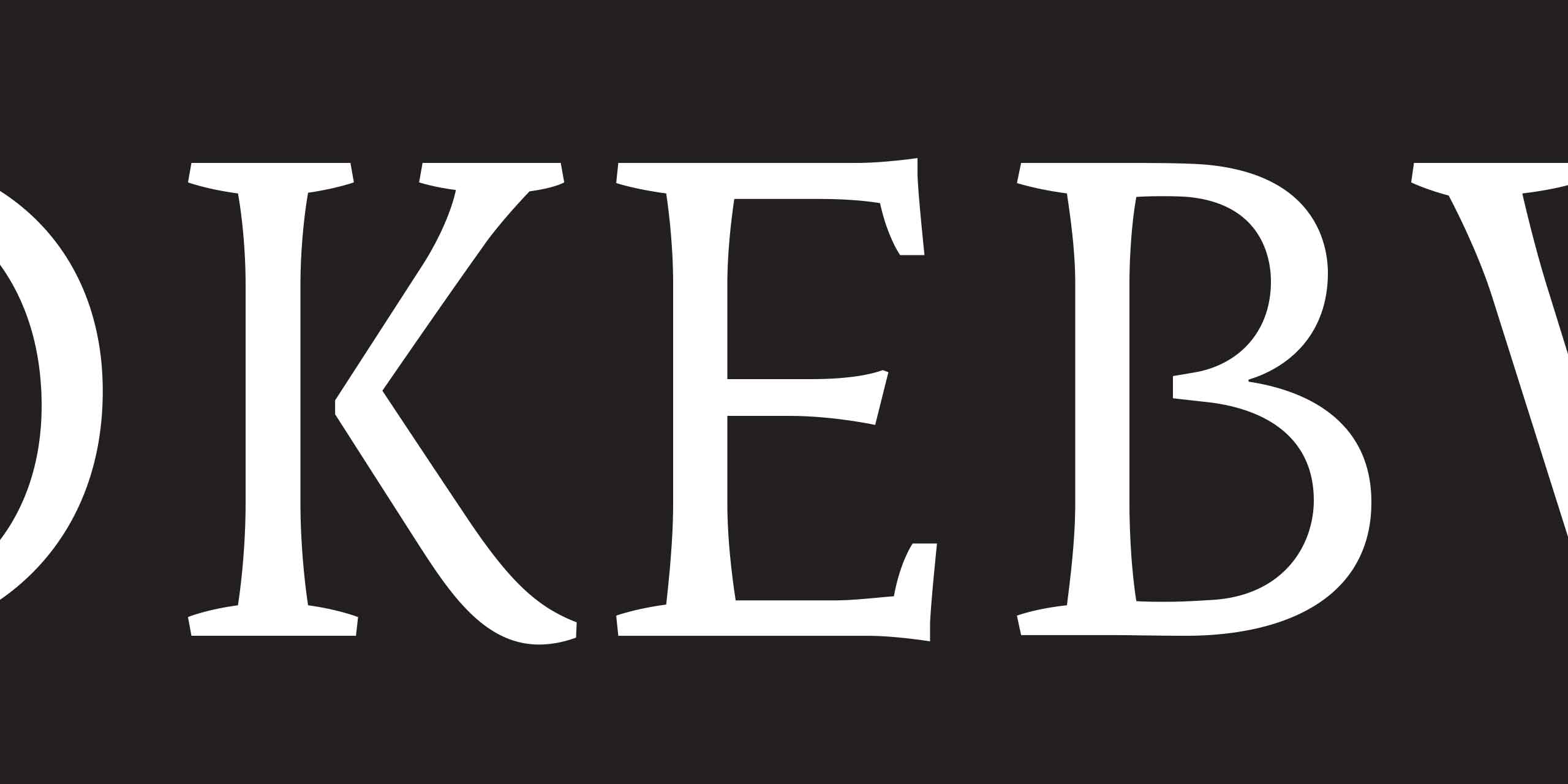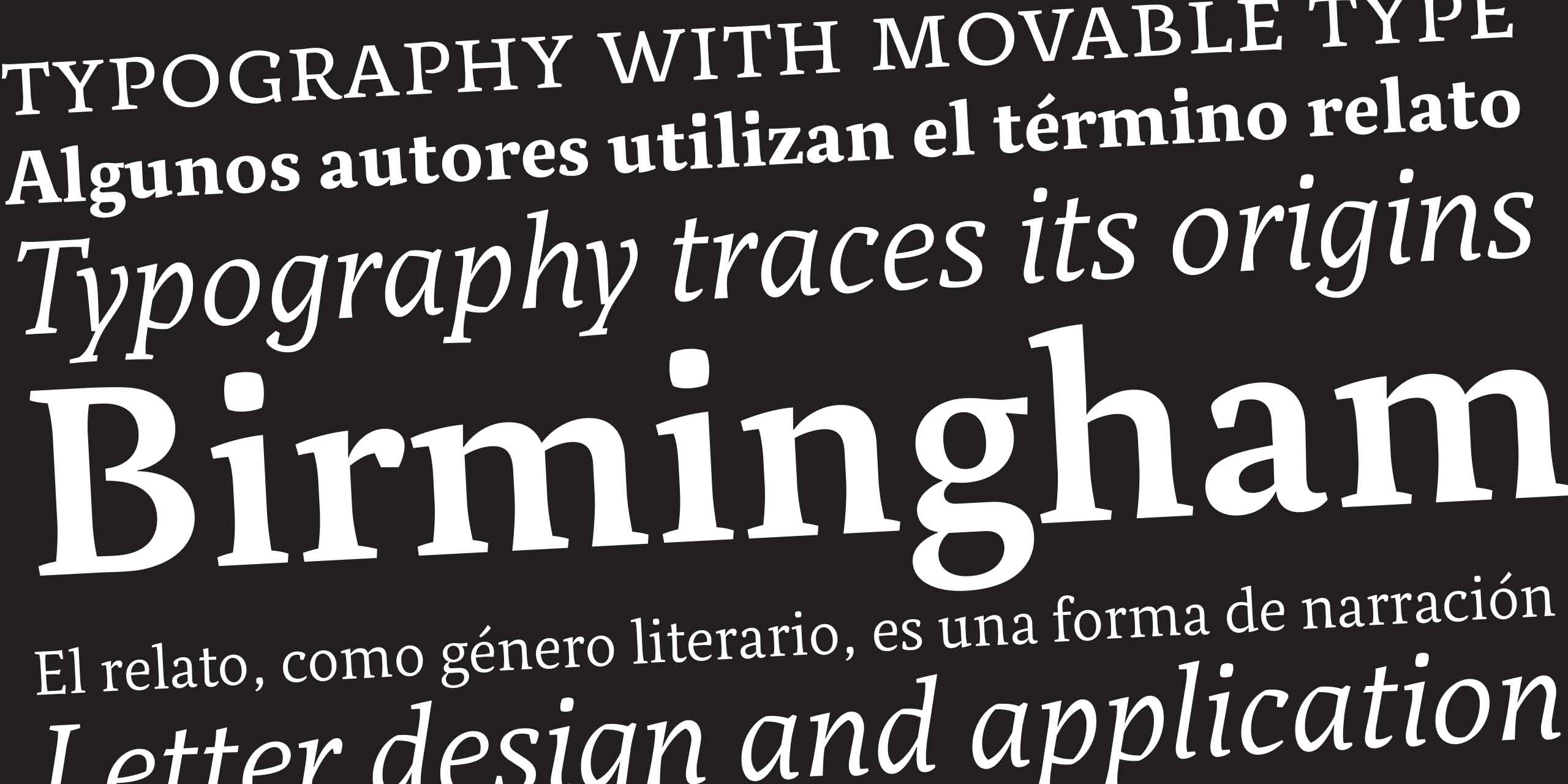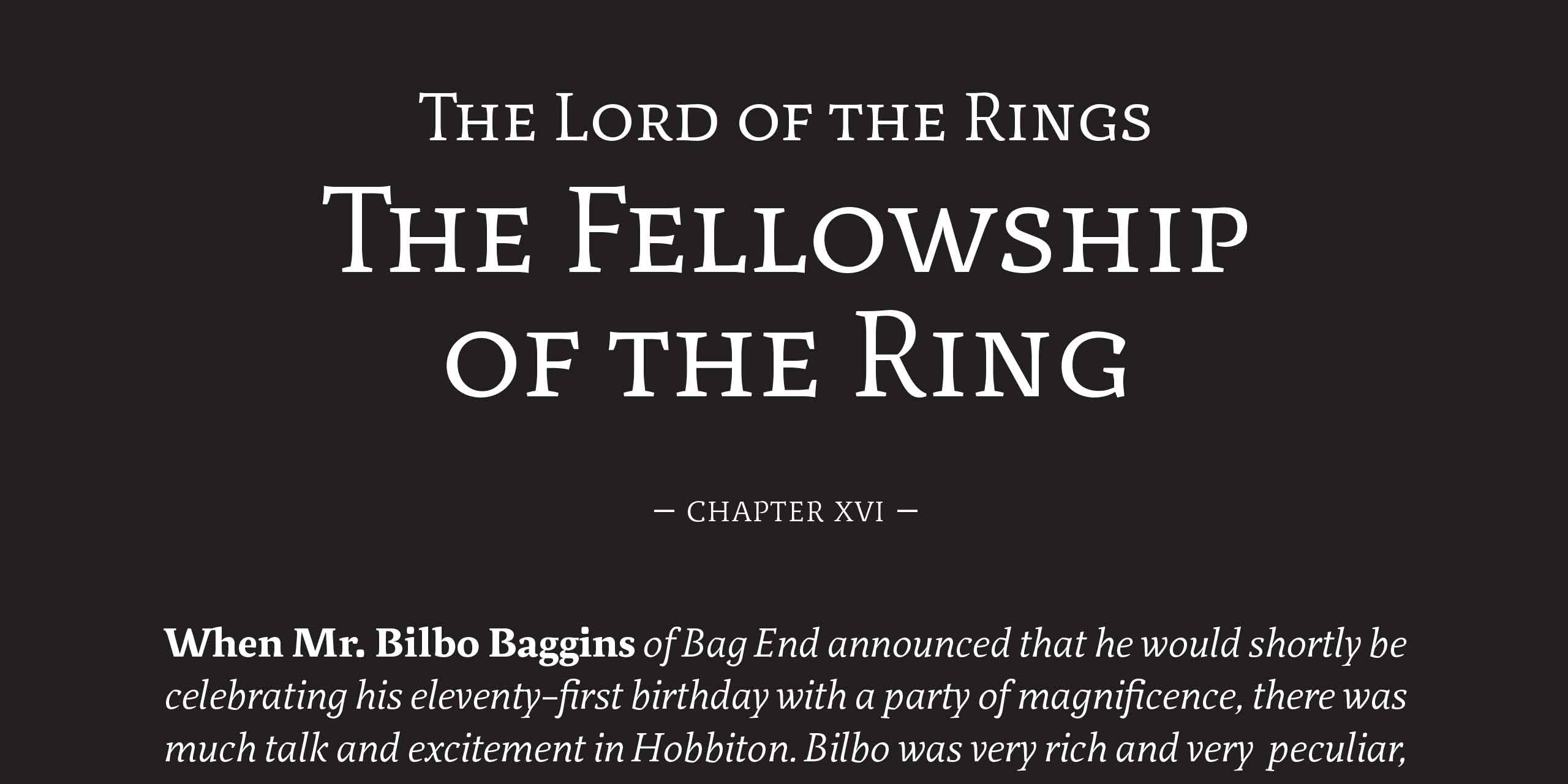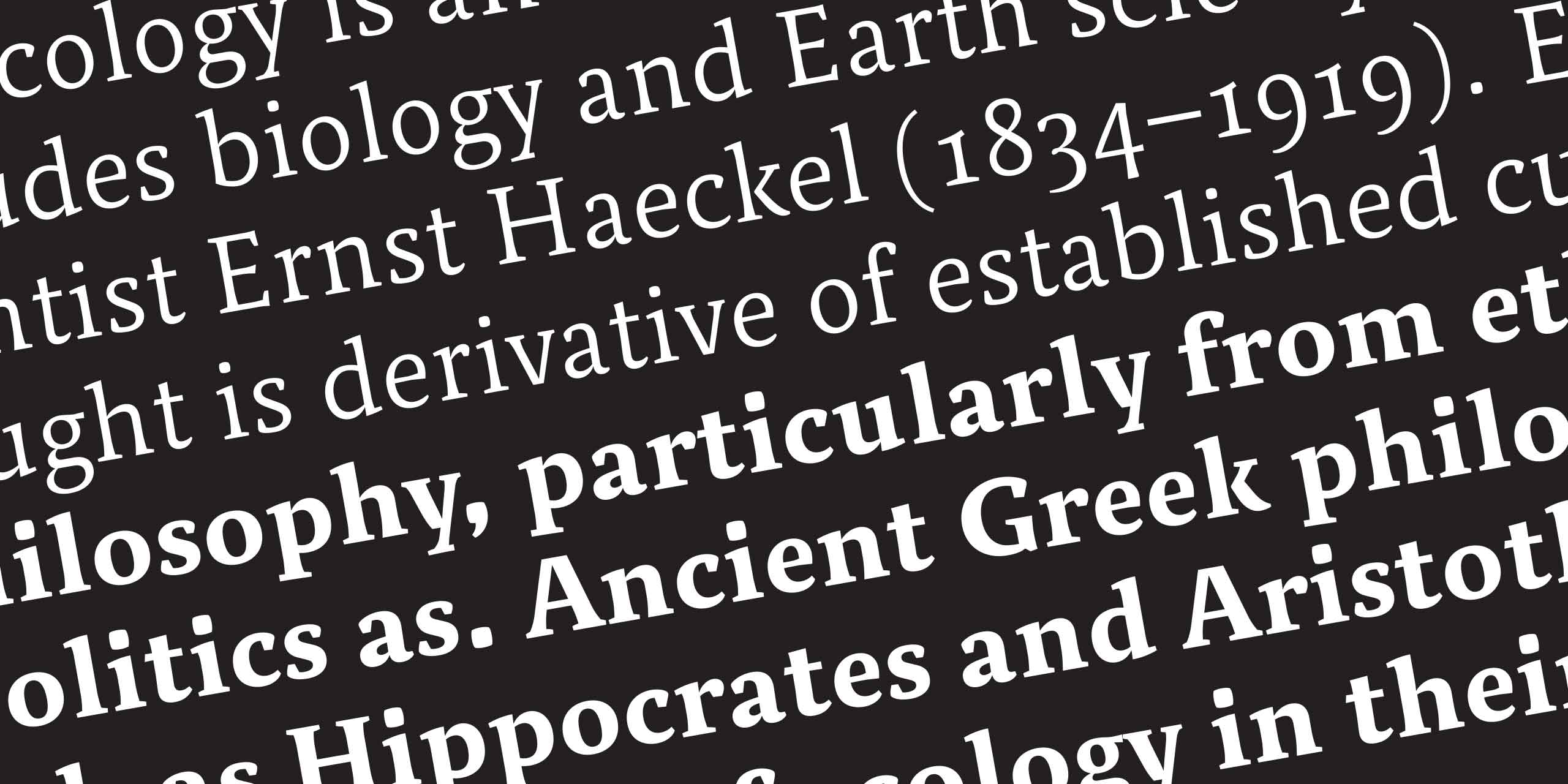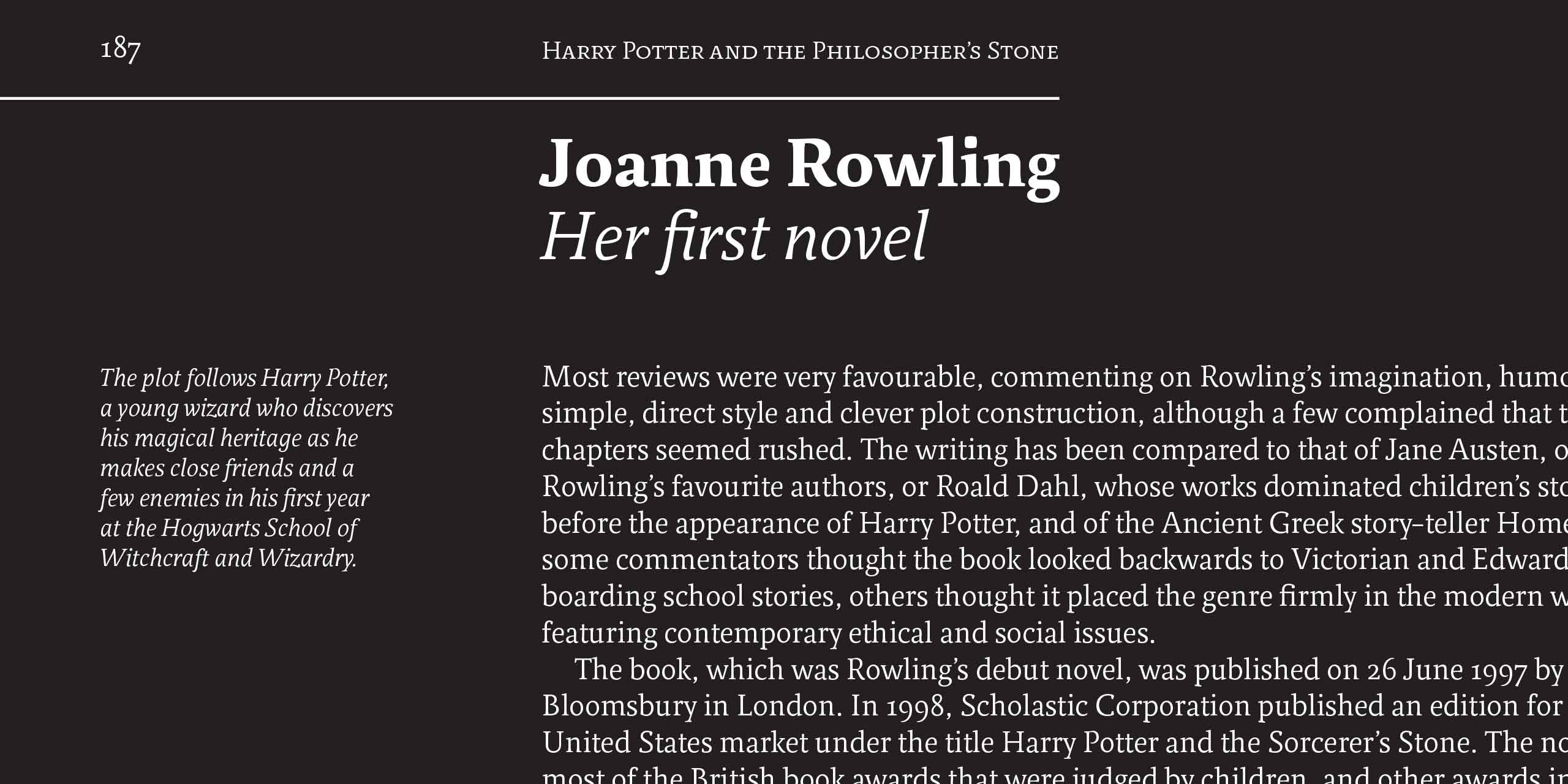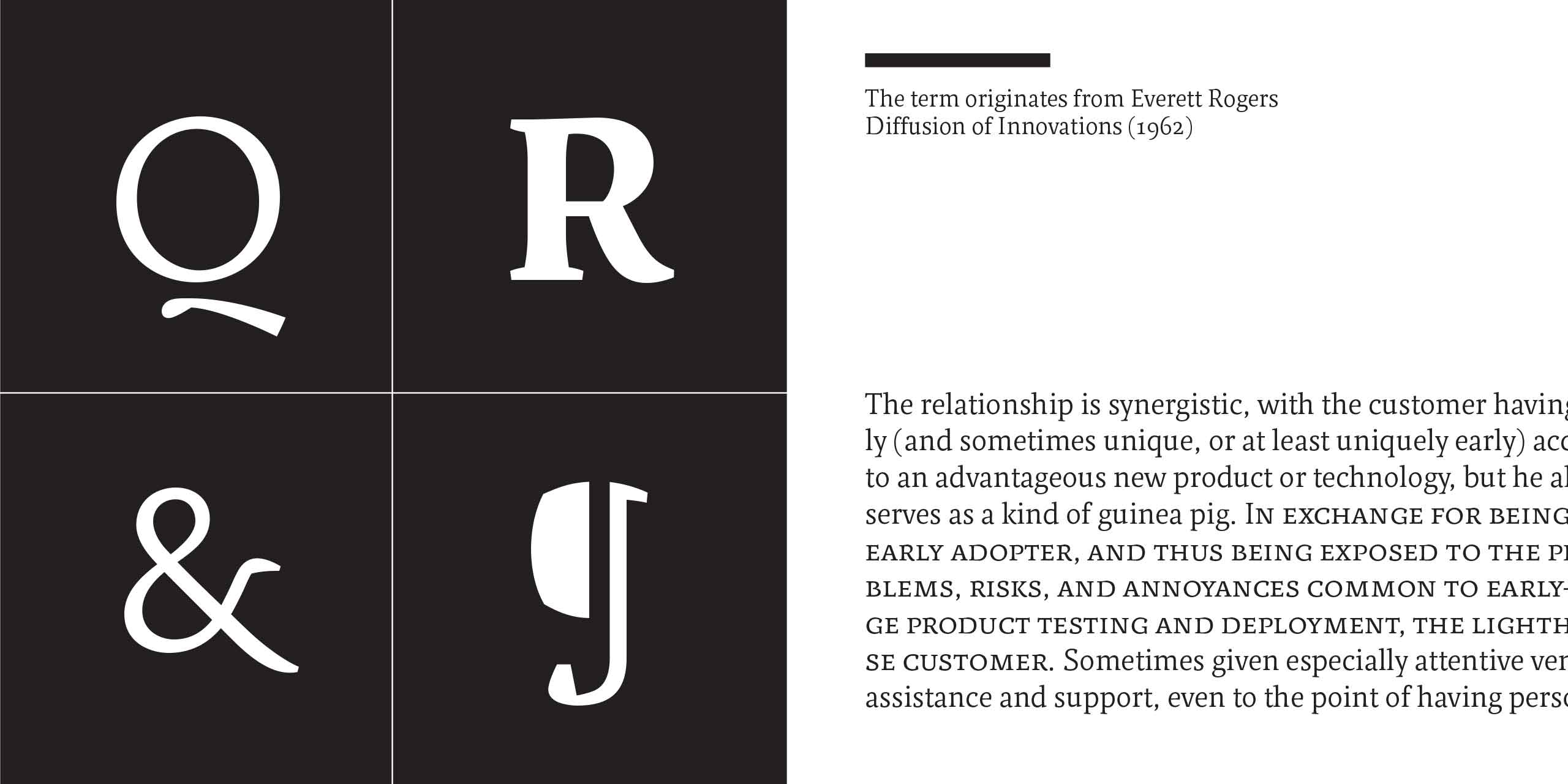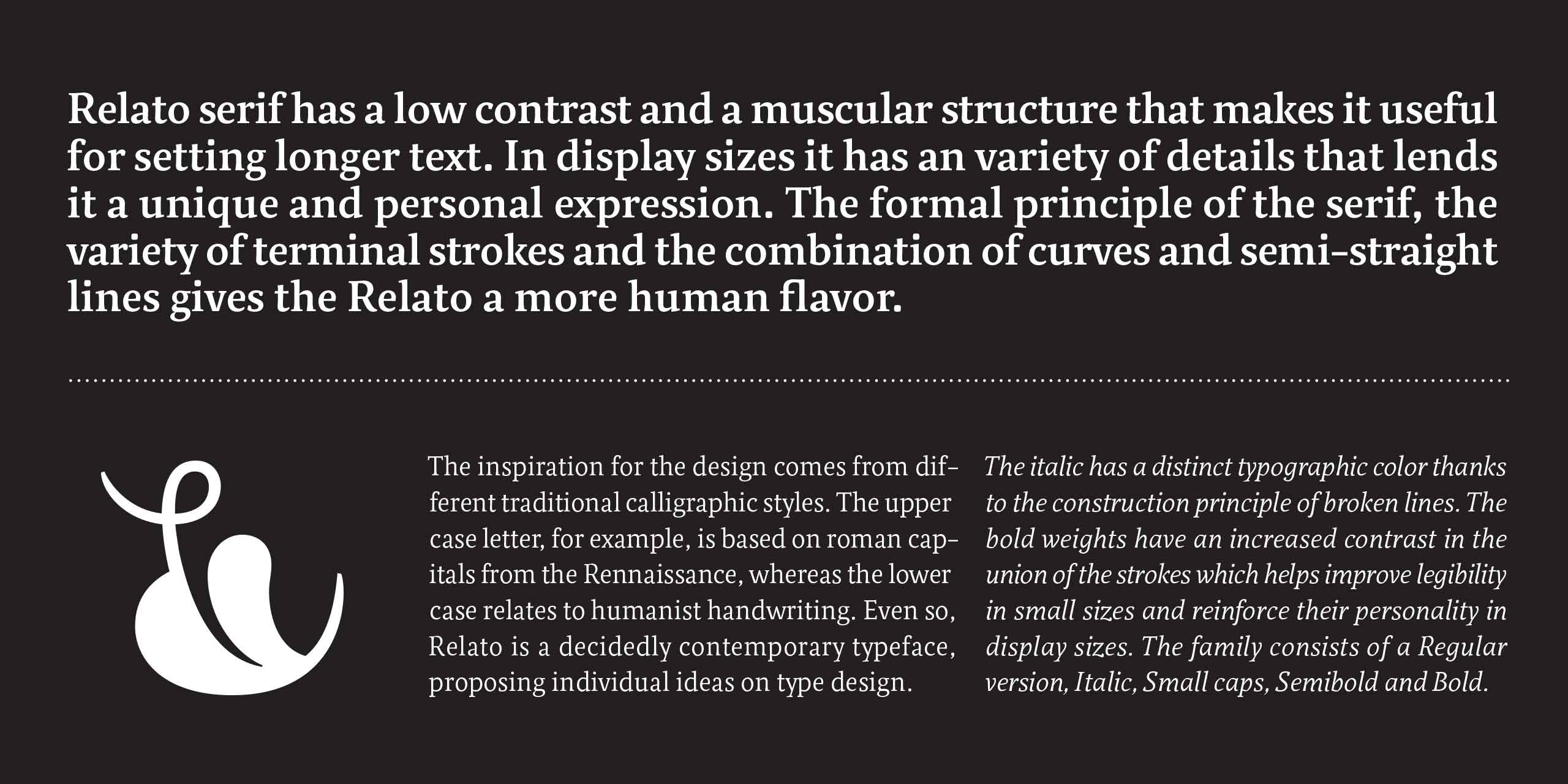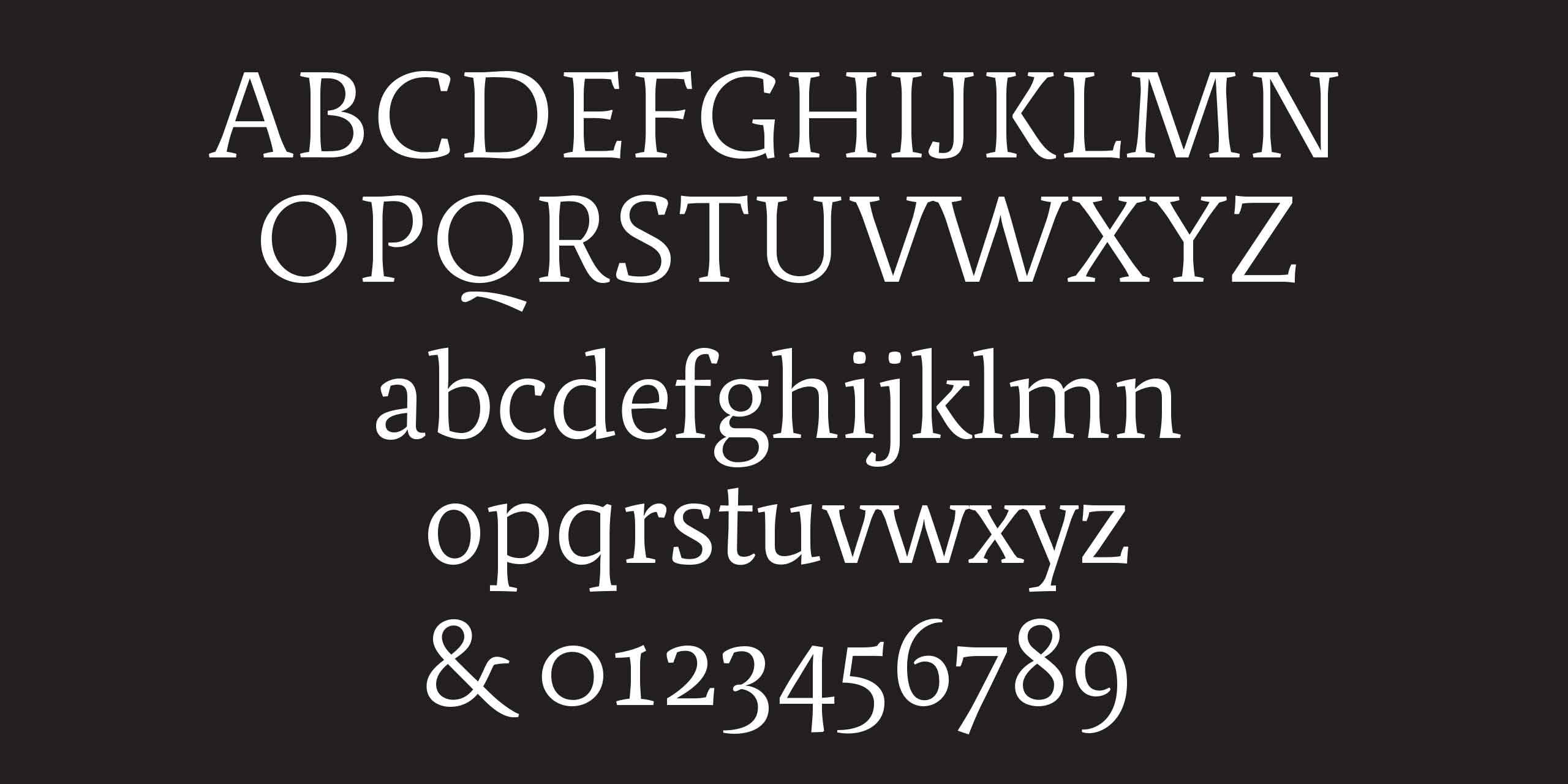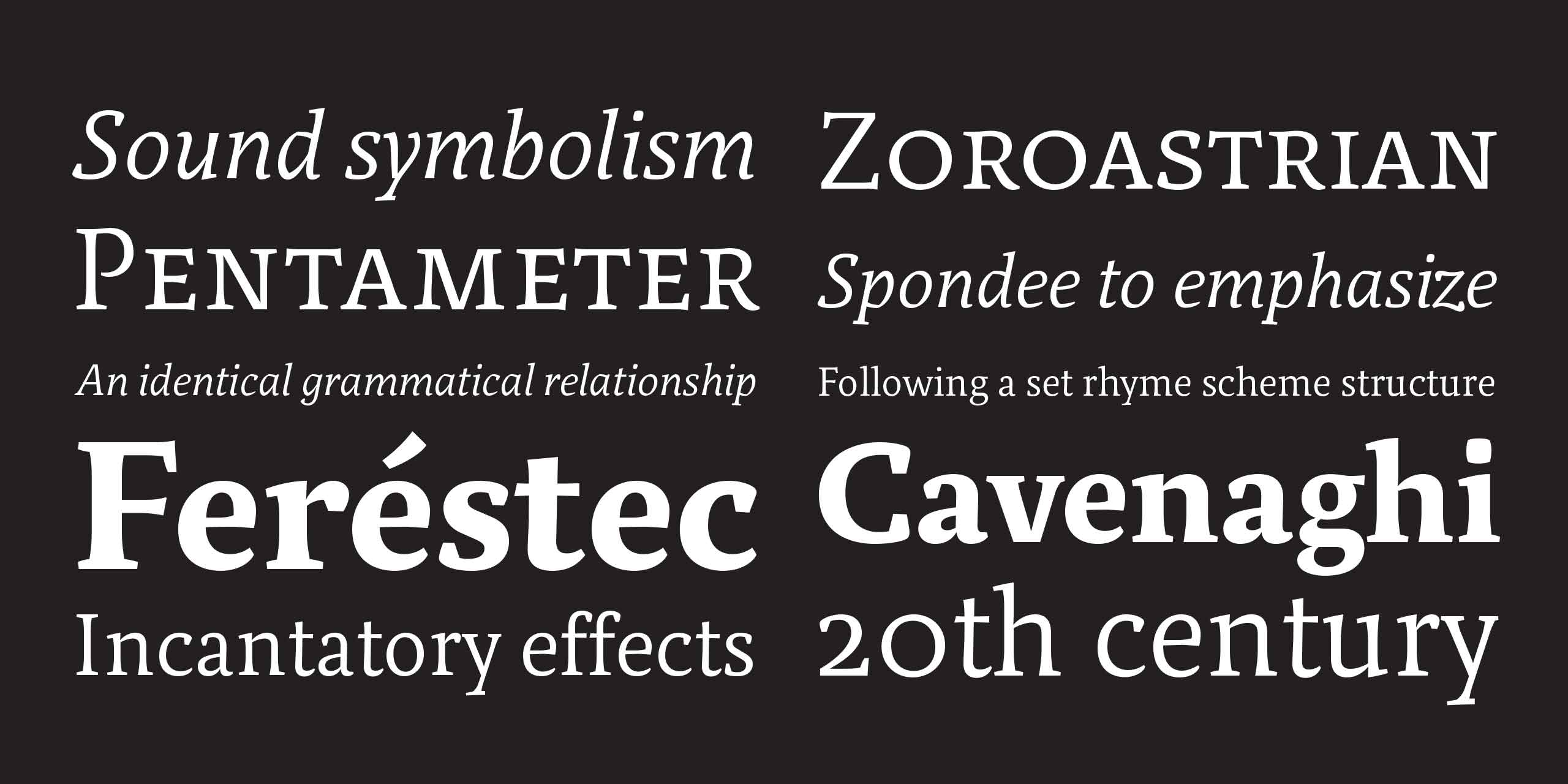
Seleccionado en los «Premios Laus 2005, Barcelona»
«Favorite Fonts of 2005», typographi.com
Relato posee poco contraste y una estructura «musculosa» que favorece su uso en textos largos y en tamaños «display» tiene infinidad de detalles que le dan una personalidad única.
Relato Serif